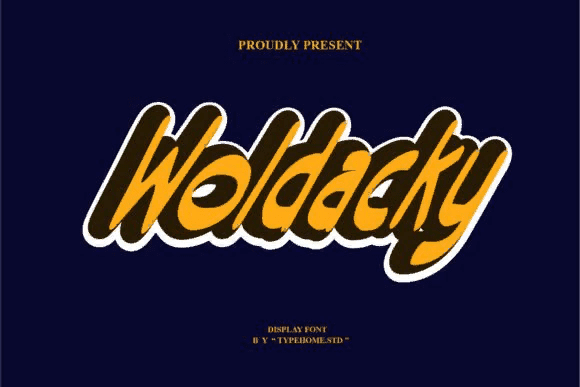
Название: Woldacky Font (2021)
Woldacky - это классный шрифт для отображения.
Вдохновленный городским искусством, этот шрифт выглядит свирепо и аутентично.
Он повысит качество каждого из ваших плакатов, листовок или печатных материалов.